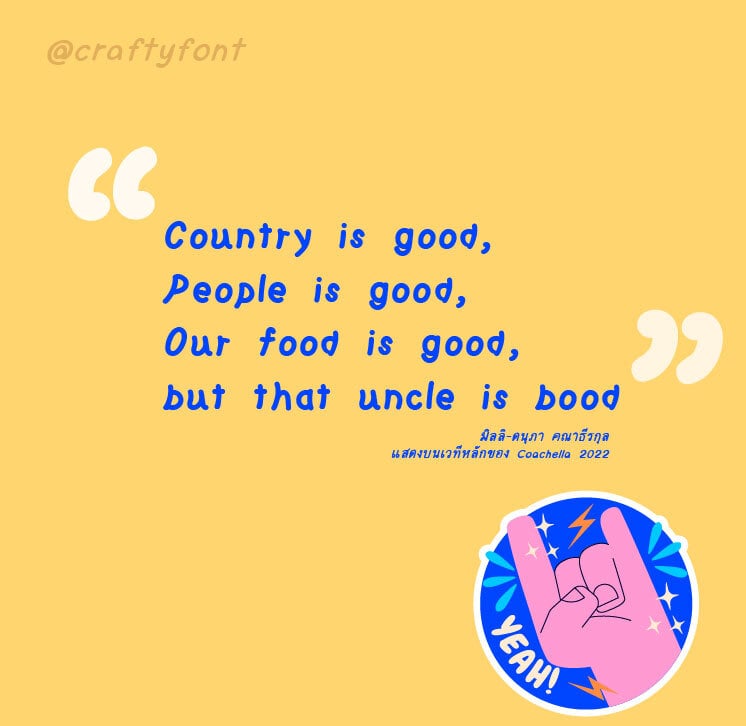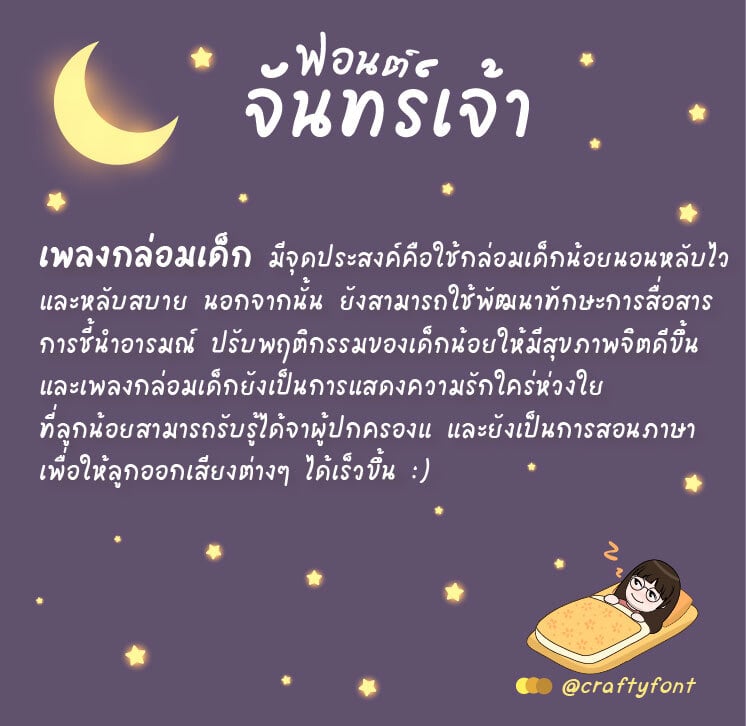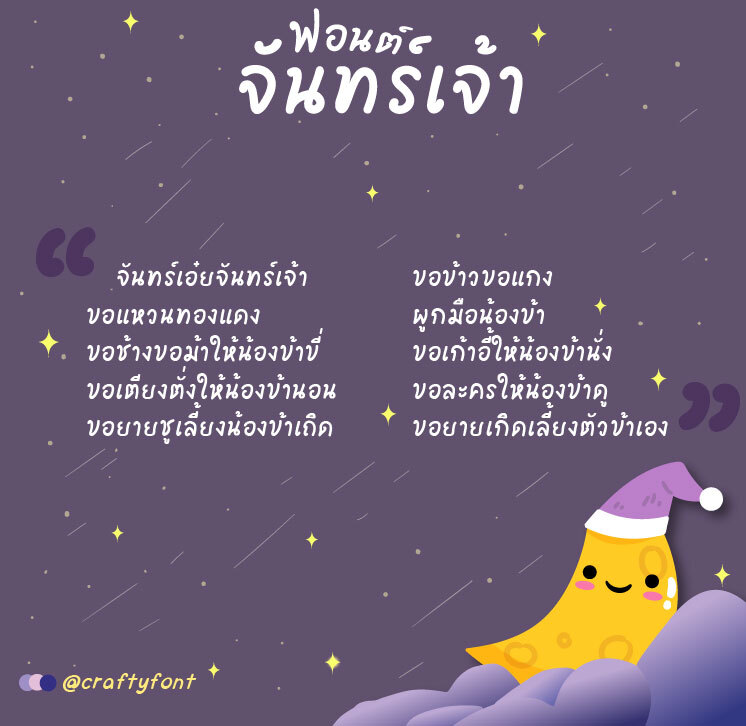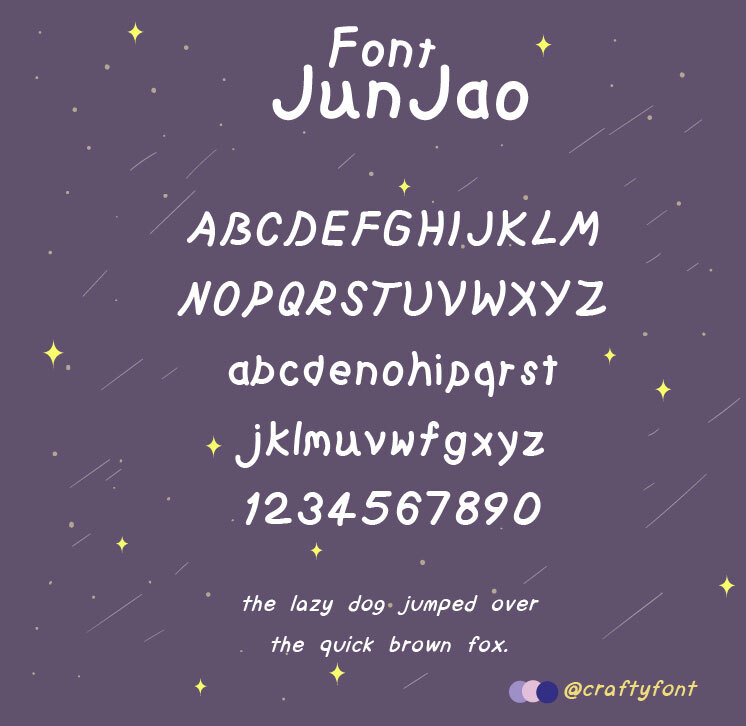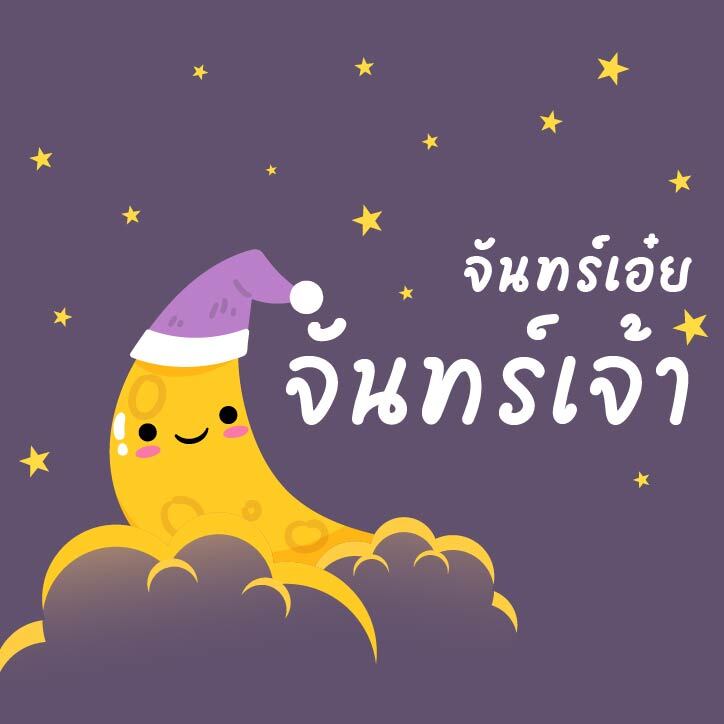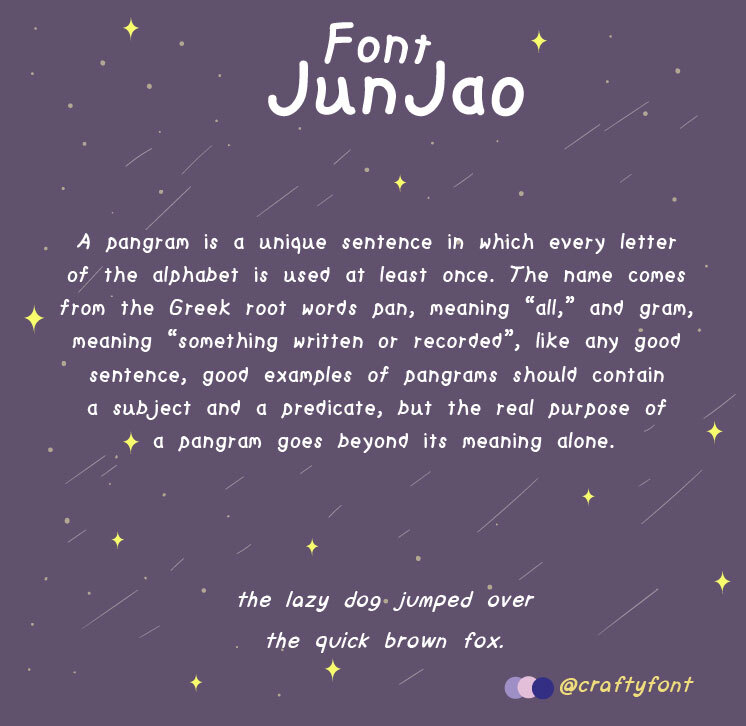
Junjao Font (ฟอนต์จันทร์เจ้า)
ฟอนต์จันทร์เจ้า เขียนตอนกำลังง่วง 😪 เลยออกแบบให้ตัวหนังสือเอียงๆ เหมือนงัวเงีย จะล้มตัวนอน เลือกใช้บรัชแบบเส้นทึบ ปรับ StreamLine ให้สมูธที่สุด เพื่อให้เส้นดูลื่นที่สุด หวังว่าทุกคนจะชอบนะคะ
ฟอนต์จันทร์เจ้ามีทั้งภาษาไทยและภาษาอังกฤษเลยนะคะ แฟมิลี่เซ็ตนี้มี 6 ขนาดด้วยกัน ทั้งตัวหนา ตัวปกติ ตัวบาง และตัวเอนสำหรับทุกน้ำหนัก สัญลักษณ์บวกลบคูณหารมีให้ใช้ครบ ฝากไว้ในอ้อมอกอ้อมใจพี่จ๋าด้วยนะจ๊ะ